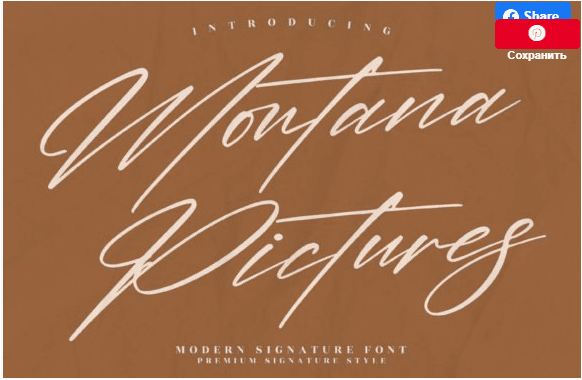
Montana Pictures Font
Montana Pictures - это стильный и неподвластный времени рукописный шрифт. Это лучший выбор для создания привлекательных логотипов, брендов и цитат. Этот шрифт имеет кодировку PUA, что означает, что вы можете легко получить доступ ко всем глифам и росчеркам!